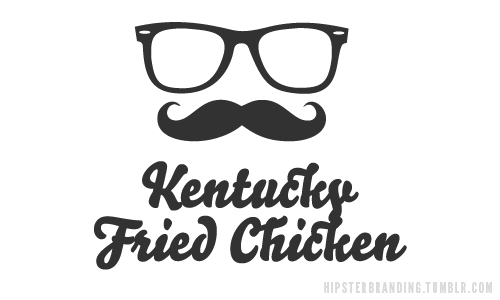
Erkennt jemand diese Schrifft?
Gerne :-) Die Ligaturen sind evtl. in der Script nicht enthalten, in der Bello Pro sind sie aber drin. Die lässt sich nur aus myfonts nicht hierher verlinken …